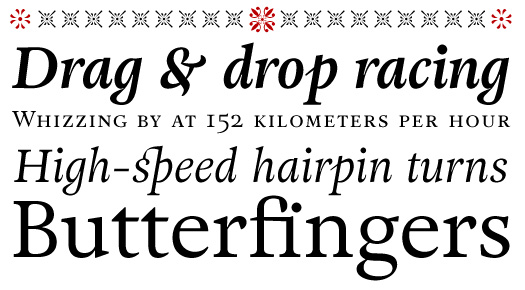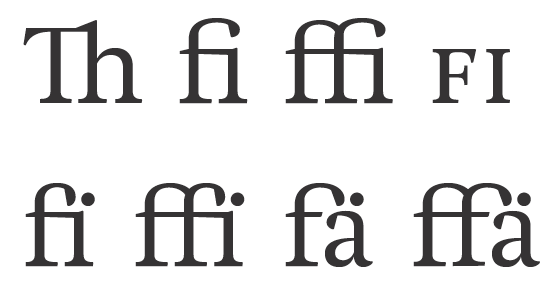
Adriane Text (Typefolio)
Adriane Text was designed between 2006 and 2007, and with
its core objectives to become an adequate text composition
and characteristics, it can be classified as a transitional typeface.
However, details in its anatomy offer a certain personality that
without it, it becomes excessively visible, in addition to an
excellent legibility in small sizes. The typeface has a medium
contrast and the axis is predominately vertical. The size of
x-height counter forms gives an extreme legible effect applied
on every typographical composition.
Adriane Text acquires two styles: regular and bold; with its
respective italic versions, small caps, tabular and proportional
figures in old style and lining, an extensive set of ligatures
for different combinations, as well as ornaments, dingbats and
several ampersands.
Liegt das an mir oder sieht die fi-Ligatur tatsächlich nach Enthauptung aus? :shock:
das ist eine f ï ligatur.
Das hätt ich nie erkannt. Ist es denn überhaupt denkbar, dass ein i-Laut nach einem f ein Trema braucht?
Die Kursive finde ich ja sehr fein (wörtlich un in übertragenem Sinne). Auch die Versalien der Roman sind gelungen. Aber die Minuskeln? Vielleicht liegt es an dieser eigenartigen Tropfenform (die fehlt ja naturgemäß in der Kursive).
ich finde die serifenformen passen teilweise nicht zu einander.
beispielsweise das kleine r und das kleine s wirken sehr
unterscheidlich. das kleine t ist sehr ebenfalls schräg. die kursive
finde ich dagegen sehr hübsch ...
8)
das kleine t ist sehr ebenfalls schräg.
erinnert mich an das t der the antiqua e von luc(as) de groot:
aber dort soll das eine optimierung für den zeitungsdruck (taz) darstellen. vielleicht hatten sie bei der adriane text was ähnliches im sinn. in dieselbe richtung geht, dass die inktraps bei einigen buchstaben extrem tief sind. kann man schön finden, muss man aber nicht :D
Ich spiele auch grade mit so einem "t" rum. Irgendwie ist das extrem schwierig richtig zu treffen. Meist ergibt sich ein Fleck im Schriftbild, und macht man es kleiner, ist das t nicht mehr als solches identifizierbar.
Der Kniff liegt wohl darin, wie breit die beiden "Ecken" des Dreiecks sind, und ob/wie die Diagonale geschwungen wird.
Heinrich hat schon Recht. Oben die fi- und die f-ï-Ligatur im Vergleich. Schrecklich sind die Ligaturen natürlich trotzdem.
schrecklich hin oder her. das ist typografische masturbation: bisschen herumgespiele, ohne dass daraus etwas sinnvolles entsteht :D
Kann man nicht für eine ffä-Ligatur definitiv eine Anwendung ausschließen? »Straffällig« müßte wegen der Wortfuge ohne diese Ligatur gesetzt werden, und auch sonst will mir nichts einfallen in dieser Sprache mit dem a-Umlaut.
yup. nicht nur diese ligatur, sondern auch andere sind für das deutsche praktisch, das heißt: wenn man eigennamen ausschließt, bedeutungslos: fb, ffb, fh, ffh, ffj, fk, ffk und ffy. ich glaube, außerhalb des deutschsprachigen raumes ahnt das keiner, weil dort bekanntlich wortfugen “overridden” werden.
ps: ich weiß ein beispiel für den (korrekten) einsatz einer ffr-ligatur – wer noch? :D
Kann es gar nicht geben, weil die Verbindung f-r keiner Ligatur bedarf. Ligaturen sind ja nur nötig, wo Buchstaben »ineinanderhakeln«. Sonst könnte man ja gleich eine Ligatur »ung« herstellen, die würde wenigstens häufig Anwendung finden.
Dieter Stockert hält Typografskis Bemerkung, es handle sich um eine f-ï-Ligatur, für einen (gelungenen) Scherz.
und warum?
Deiner Frage entnehme ich, daß ich mich geirrt habe, tut mir leid.
Zur Erklärung: Als unbedarftem dtp-Autodidakten ist mir eine solche Ligatur (oder auch eine f-ä-Ligatur) bisher weder untergekommen noch hätte ich es für möglich gehalten, daß eine solche Ligatur existiert. Es ist ja schon in gewisser Weise 'gewagt', eine f-i-Ligatur herzustellen, weil damit doch ganz erheblich in das, was die Form des i ausmacht, eingegriffen wird, aber da halte ich es noch für gut nachvollzieh- und begründbar, schließlich läßt sich der i-Punkt im 'Tropfen' des f noch erkennen. Aber daß nun beim Trema die beiden Punkte so unterschiedlich konstruiert sein sollten, ging über meinen Verstand. Deine Erklärung für das, was in meinen Augen eine selten groteske Verirrung darstellt, konnte für mich nicht anders als witzig gemeint sein. Jetzt weiß ich's also besser.
Ob es einer Ligatur bedarf oder ob es sie gibt sind doch zwei verschiedene Fragen. Eine Ligatur ist doch nur eine Verbindung aus Buchstaben, die Aufgrund von Kollisionsgefahr der Einzelformen, schreibtechnischer Gegebenheiten, oder aus schriftgestalterischem Übereifer entstehen kann.
Ich habe z.B. in einem Schriftentwurf von mir eine ffr-Ligatur drin. Warum? Es ist eine Nachbildung einer Kupferstecherschrift, wo jeder Strichansatz Mühe macht. Da bietet es sich an, die Querbalken der f durchzuziehen, und gleich im r fortzusetzen statt abzusetzen, neu anzusetzen, den Anstrich des r zu machen, und dann die Senkrechte. So ensteht die, ohne dass sie aufgrund von Kollisionsgefahr der Formen von nöten wäre.
genau bei kauffrau gibt es besagte wortfuge
und eine ligatur ist fehl am platz ...